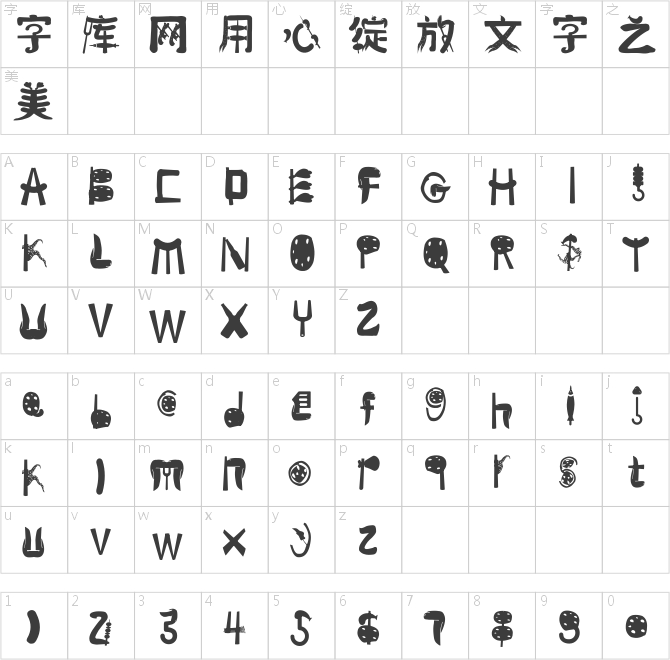
逐浪海鮮排檔擼串體 詳情頁
一款擬物的漢字,因為燒烤夜宵店老板要求而產生這個創意,盡量的擬物,按gb2312規則編碼,特別適合海鮮店、排檔、烤串店使用。
1、因而為燒烤、擼串字體,所以處理過程中可增加一些“咬痕”如丁字一橫。有如三五好友一同擼串,更為真實。
2、本案大多偏旁都以燒烤串外形演變而來。
3、烈字,加上少許“熱氣”外觀,猶如剛出爐的烤串,顯得更為真實。
擼字,右邊的田字左上角,有一張嘴巴,擬人化形象非常逼真。
民以為食為天,食以味為先。
一款以夜宵擼串為主題的字體,其精髓在于如何應用場景以及擬物的真實,并不失去可識別性,這需要研發與設計團隊付出極大的心血。
為此,逐浪字庫人,考量了多種場合以及識別距離,引入了unicode 13標準,進行了矢量化的識別,支持高清展示。
整個字庫,不僅是漢字,英文、標點符號以及橫豎排版,均進行了專業的精良設計與生產,支持嚴謹的國標產品線。
整個字庫的生產歷晚一年,先后考察了13個省份(自治區)以及港臺地區餐飲應用場景,進行了多場景識別與試驗,最后成型,具備良好的應用與擴展功能,提供矢量化樣本與全庫應用,工藝精良,風格特別,原創與開拓并舉,引領中國與華文字庫產業進入全新擬物時代。